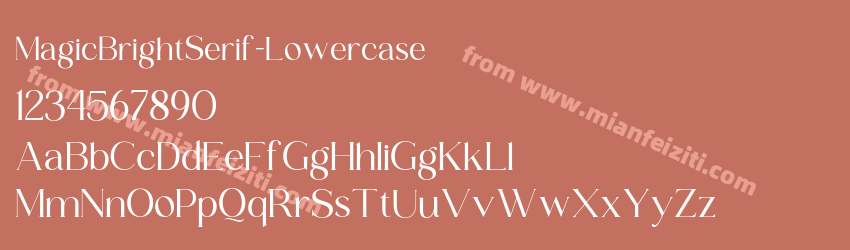
Magic Bright Serif Lowercase
字体名称: Magic Bright Serif Lowercase
Postscript名称: MagicBrightSerif-Lowercase
本款“Magic Bright Serif Lowercase”是一款书写很新颖的字体,字体大方,适合各种设计作品使用!欢迎下载!